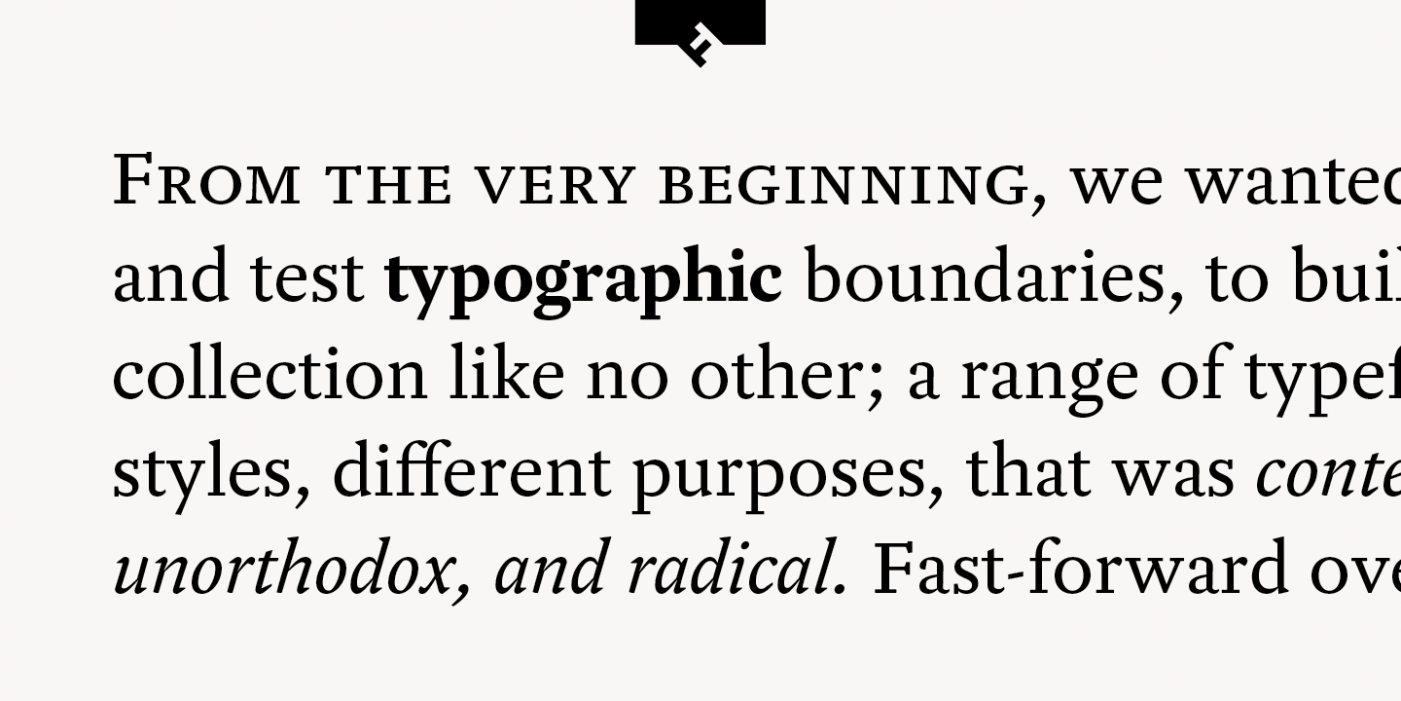
Schriftkombi: Gill Sans & ?
Welche Schriftkombination schlagt ihr für die Gill Sans vor?
Die Schriften sollen vor allem im Print (überwiegend Brochüren) aber auch digital gemeinsam benutzt werden – Gill Sans als Headline- sowie Fließtextschrift, dazu gesucht wird noch eine passende Serifenschrift für Fließtext. Dieser wird in zwei Sprachen sein; Trennung der Sprachen evtl durch regular/italic Schnitte?
Ist die Cheltenham ein Versuch wert?
Minion Pro wurde mir empfohlen, doch scheint mir diese nicht geeignet.
Joanna Nova, das wäre eine Schrift, die ebenso wie die Gill, nach Eric Gills Entwürfen gefertigt wurde.
Meine erste Wahl zur Ergänzung der Gill Sans wäre auch die Joanna Nova. Diese ist natürlich recht eigenwillig mit ihren schmalen Slab-Serifen. Soll das Schriftbild des Fließtextes eher in Richtung einer klassischen Antiqua gehen, würde ich wohl auf die Bunyan zurückgreifen (2016 digitalisiert von Patrick Griffin und Bill Troop für Canada Type) – darin steckt immer noch genug Eric Gill, um der Gill Sans stimmig zur Seite zu stehen.
Minion Pro wurde mir empfohlen, doch scheint mir diese nicht geeignet.
Warum? DAs wäre ganz gut zu erfahren, damit man weitere Tipps geben kann ... Auch wären ein paar Bilder der bisherigen Ideen nicht schlecht, dann muss man sie nicht selber suchen ;-)
Die Joanna Nova sowie die Yoga, scheinen mir ganz passend und geben dem Ganzen eine gewisse Frische. Ich werde ein Versuch mit diesen Schriften starten – falls ich noch Fragen habe, komme ich auf euch zurück!